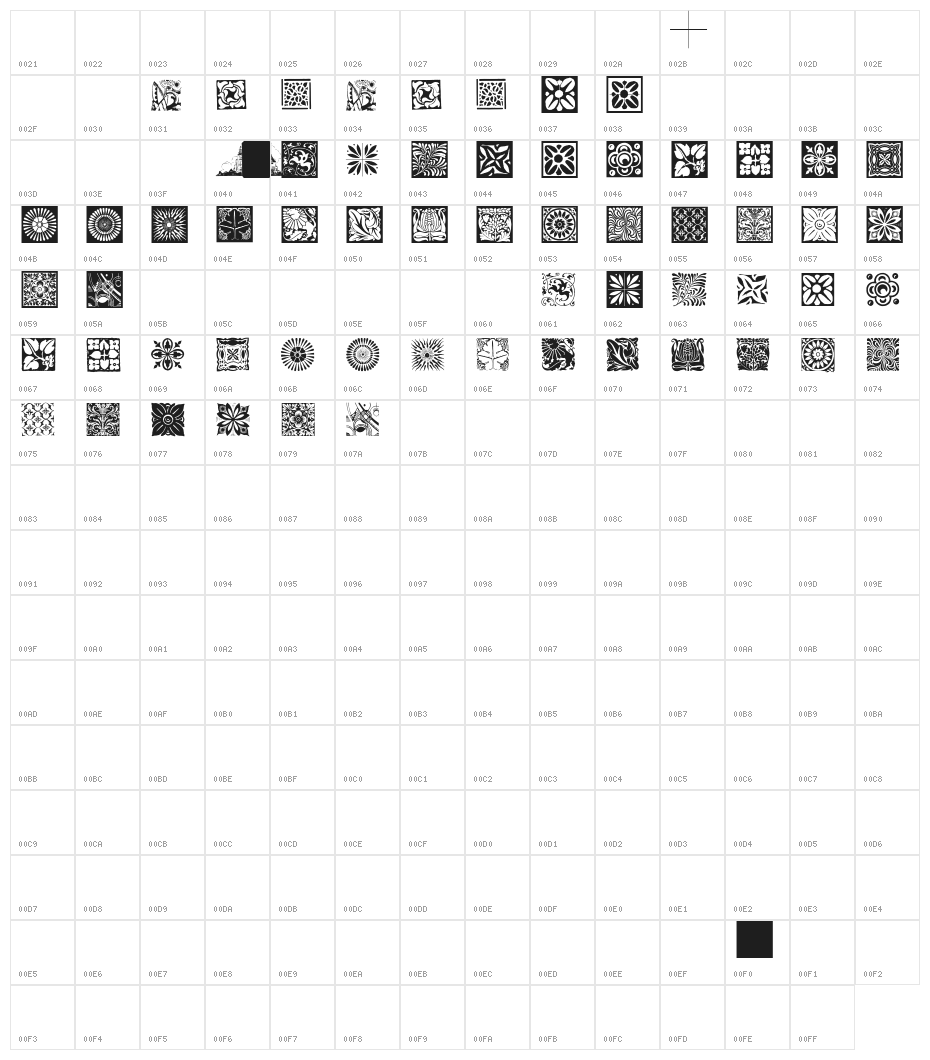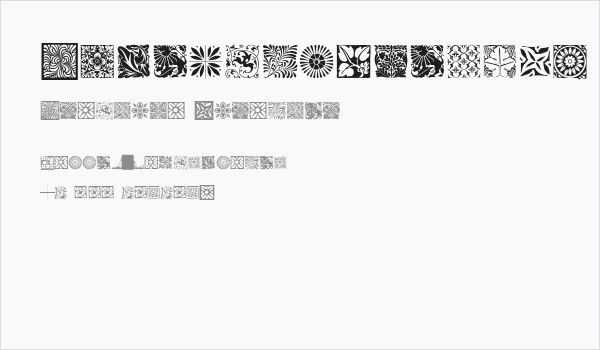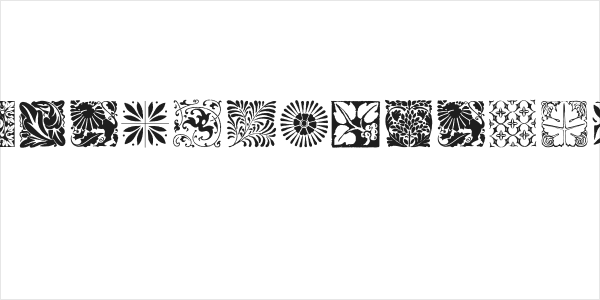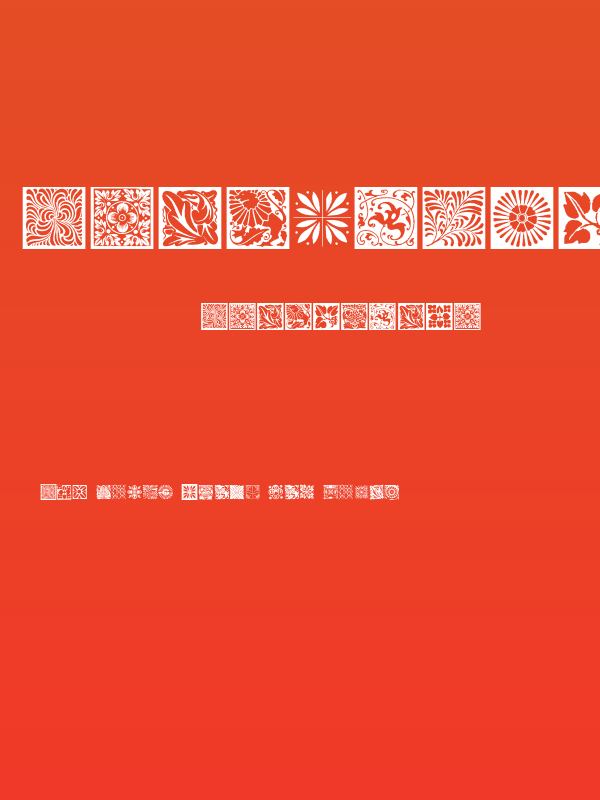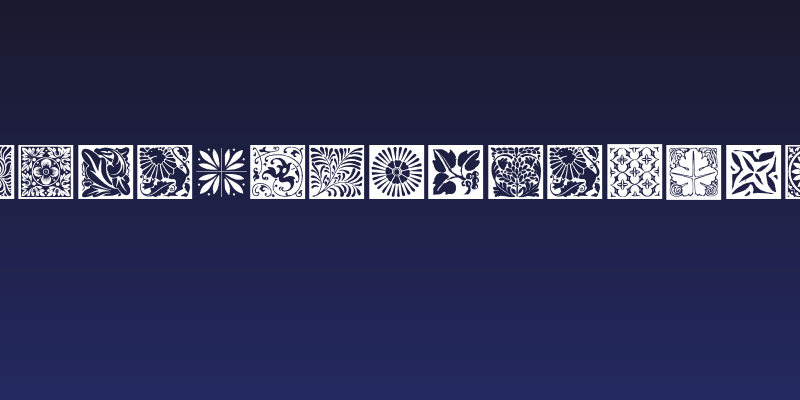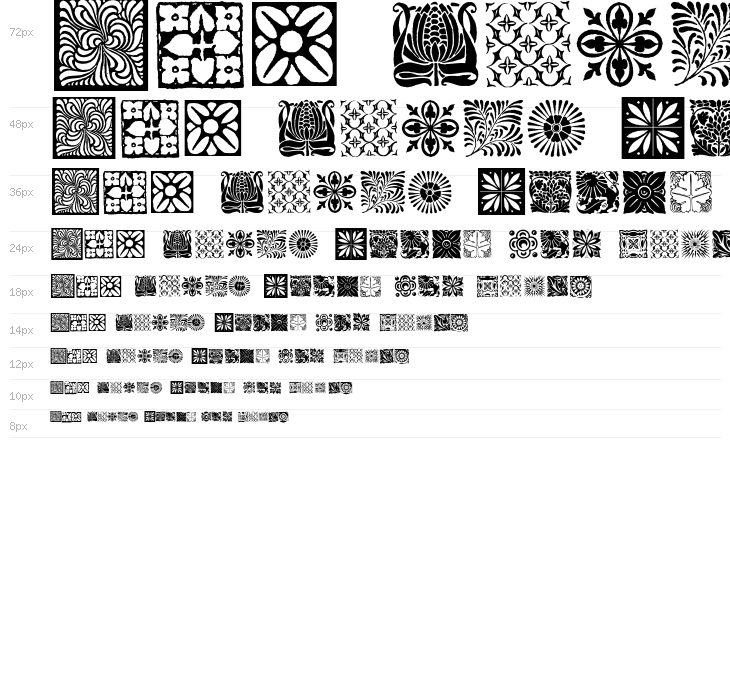
TypoBackgrounds Font
✎ Dingbats
| Gesamtstil | Decorative, Vintage, Ornamental |
| Anwendungsfall | Headlines, Logos, Decorative elements |
| Vorgeschlagene Projekte | Posters, invitations, branding for restaurants or cafes, packaging, decorative borders, event materials. |